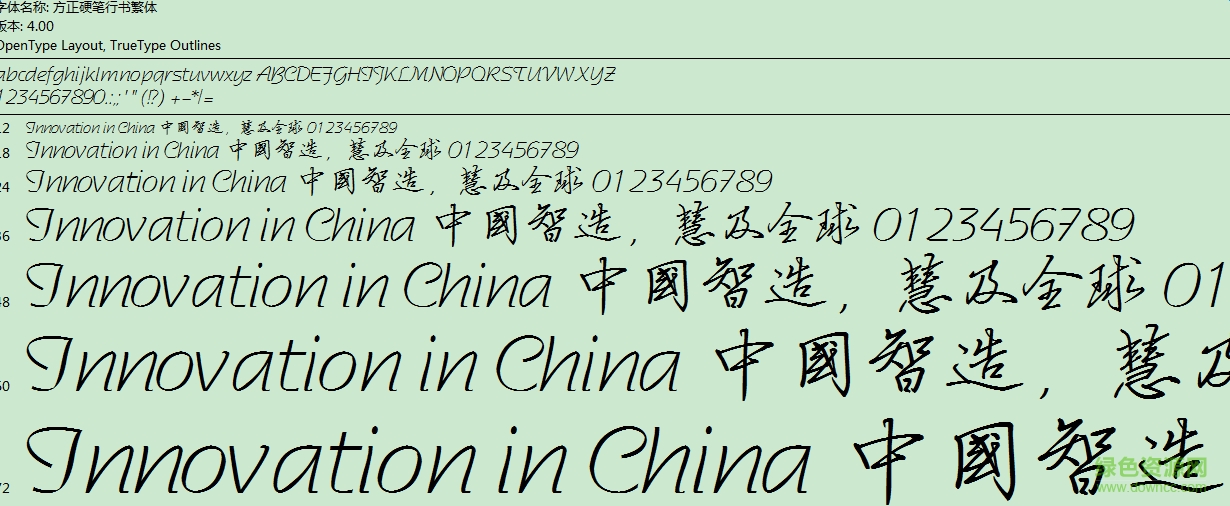
繁體行書字體大全收錄了胡敬禮毛筆行書繁、方正硬筆行書繁體、禹衛(wèi)書法行書繁體、漢鼎繁行書等一系列漂亮的繁體字體,筆觸和諧,結構舒展,字里行間瀟灑肆意,歡迎大家免費下載!
一把方形的字傾斜成斜邊形,從險勢中增強字的動勢;
二是采用倚正相依手法,使字體活潑穩(wěn)定又不東倒西歪;
三加大橫、豎畫的傾斜度,增強整個字的動勢;
四采用虛實對比手法,使字體取得動而平衡的要求。